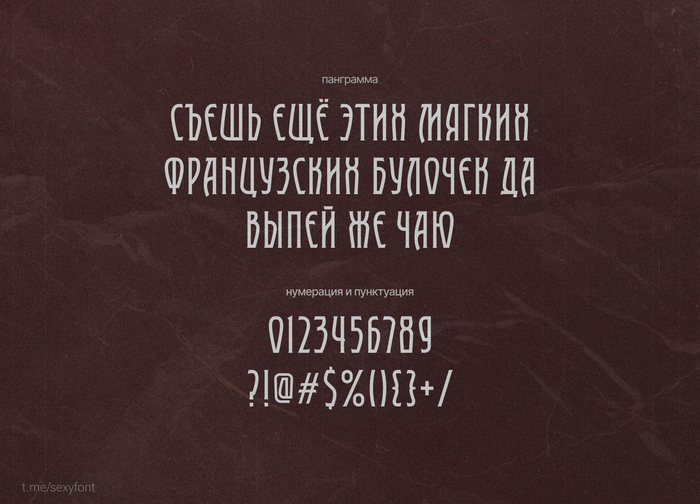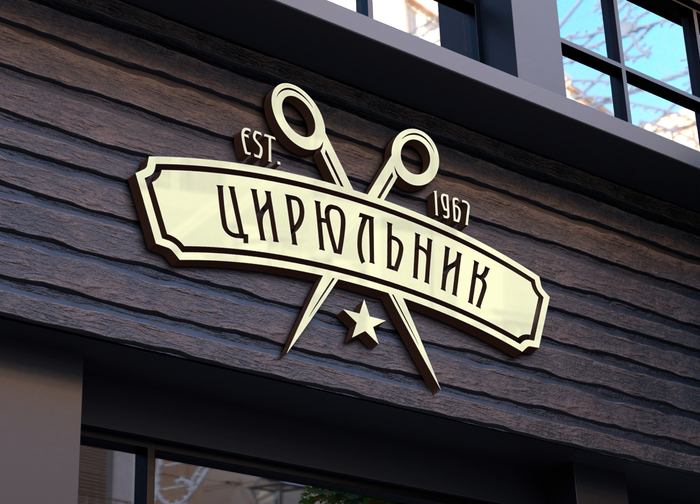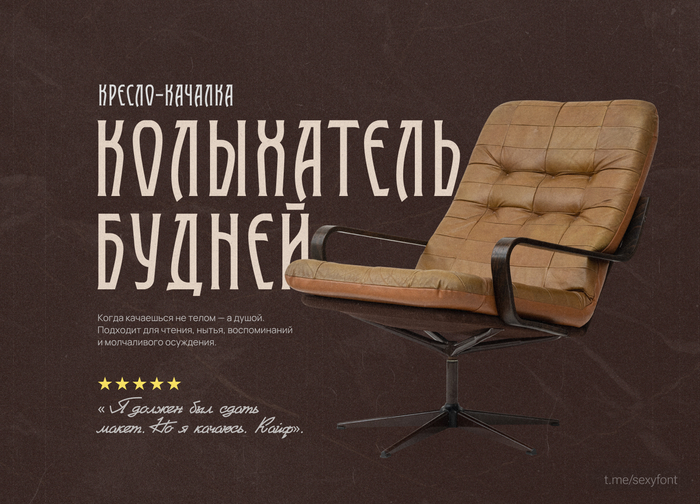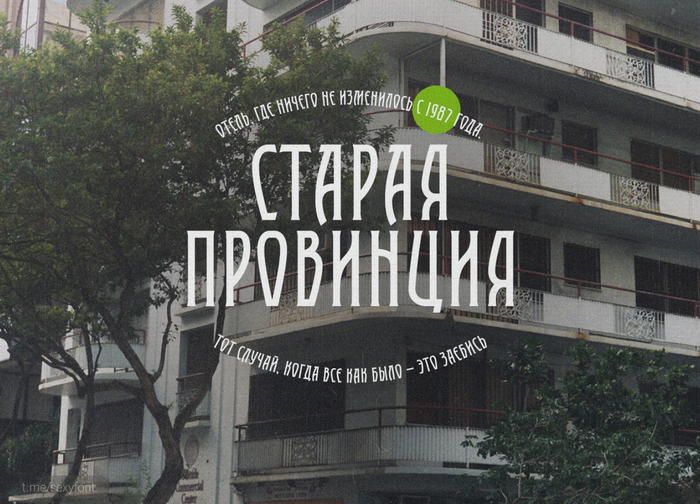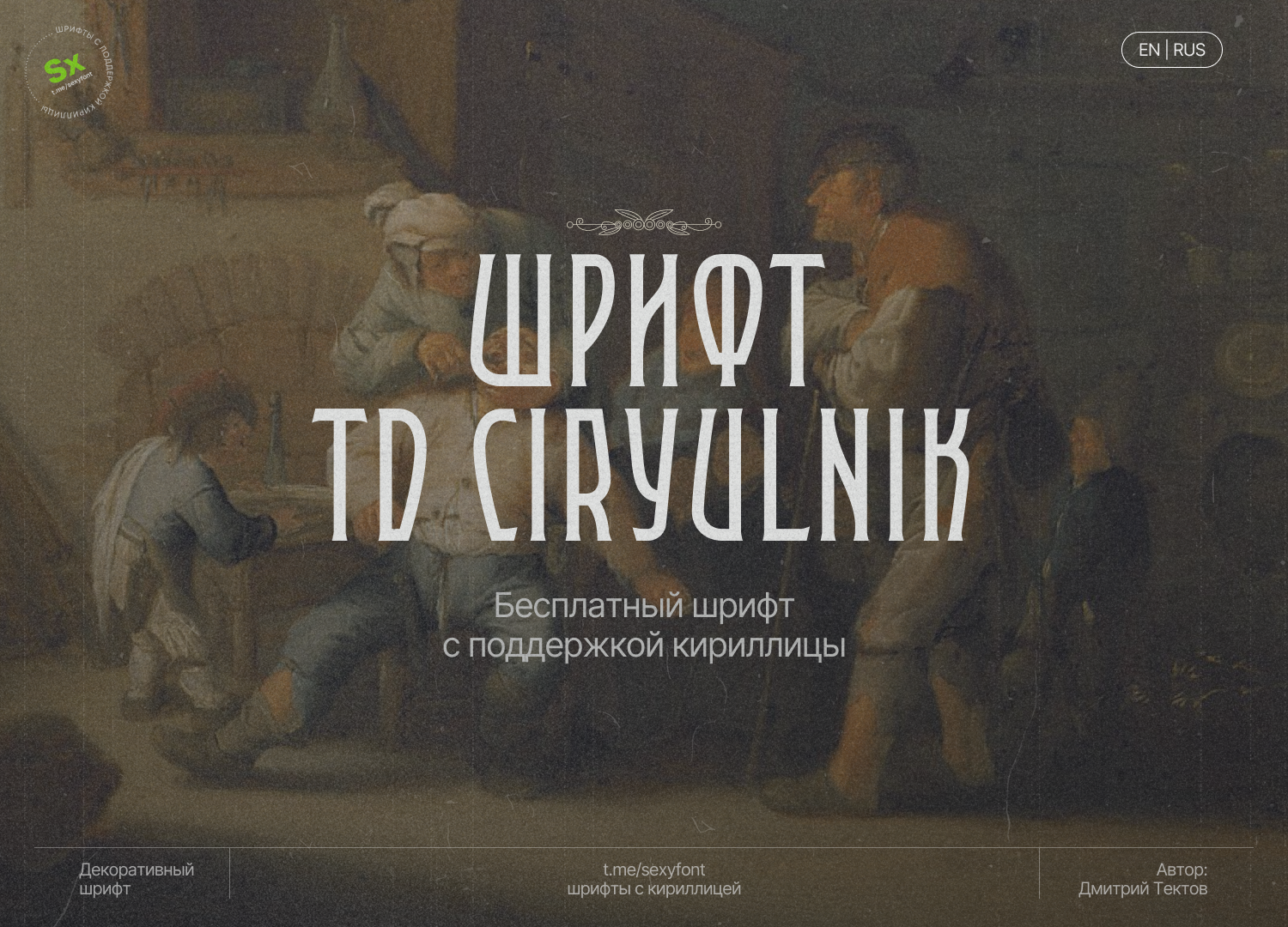
Бесплатный Шрифт TD Ciryulnik⁠⁠
😎 Шрифт TD Ciryulnik. Очередной шедевр от Дмитрия Тектова.
Подойдет для кучи сфер: Барбершопы, театральные афиши, антикварные магазины, упаковка крафтового мыла, настойки и мази «от всего», Тату-салоны с «олдскул» вайбом, Плакаты на дачу: «Осторожно, злой дед»